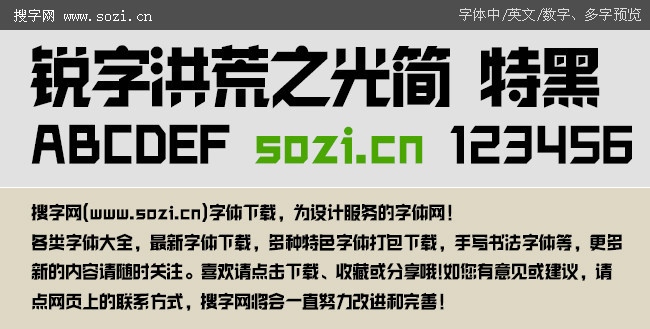
銳字洪荒之光簡(jiǎn) 特黑
搜字網(wǎng)提供一款銳字洪荒之光簡(jiǎn) 特黑中文字體下載,銳字洪荒之光簡(jiǎn)是銳字工房洪荒之光簡(jiǎn)系列藝術(shù)在體,字體穩(wěn)定,優(yōu)雅,堅(jiān)固,看起來(lái)非常漂亮,整體效果非常均勻,可以應(yīng)用于廣告設(shè)計(jì)、名片設(shè)計(jì)、包裝印刷、產(chǎn)品設(shè)計(jì)等應(yīng)用。(本字體為個(gè)人非商用版,商用請(qǐng)聯(lián)系作者購(gòu)買授權(quán))